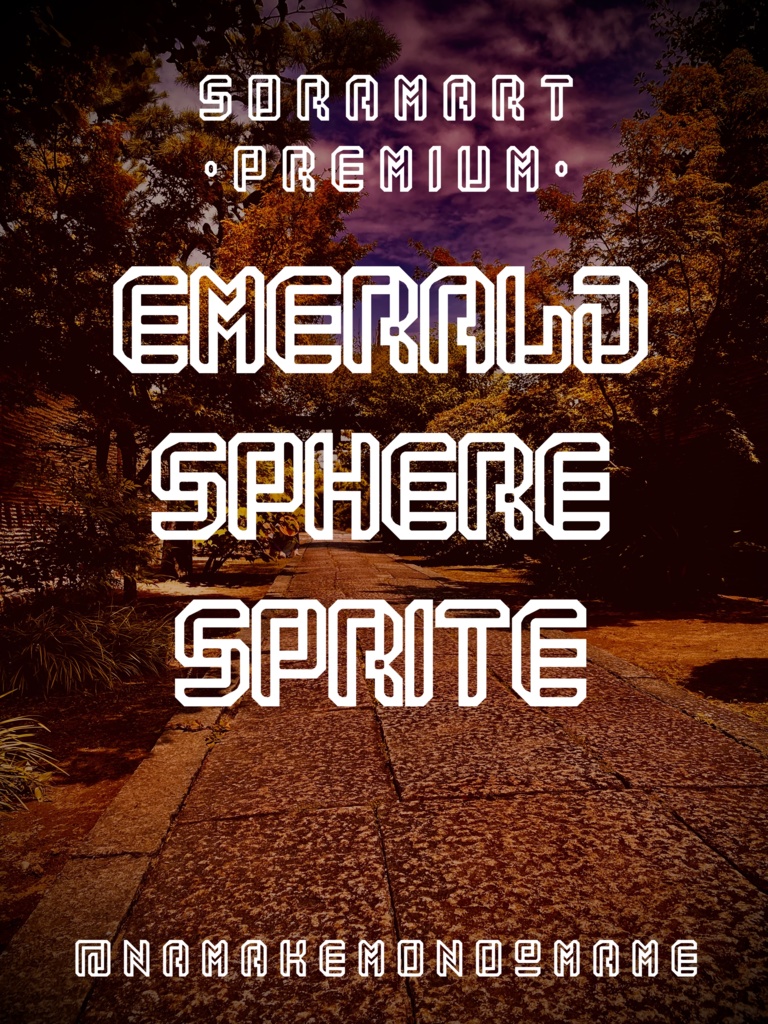
そらマートフォントデータ”Emerald Sphere Sprite”Digital2,500 JPYAdd to CartBuy a GiftAbout Gift八角形シルエットのポップ調フォントに白抜き加工を施した "Emerald Sphere Sprite" です。 「TrueTypeフォントファイル」という形式です。 ダウンロードした後、Zipファイル内のデータをインストールしてお使いください。 このフォントは商用利用可となっております。 お客様の制作・創作活動のお役に立てれば幸いです。 ※使用上の注意事項などは、添付のReadmeをお読みください。 ※このフォントは、有料販売専用商品です。そらマートVisit FANBOX!Fontsフォントデータ”Eight-bit Quest Wide”そらマート0 JPYFontsフォントデータ”Eight-bit Quest”そらマート0 JPYFontsフォントデータ”Tonik Crate”そらマート0 JPYFontsフォントデータ”Vapor Sprout Edge”そらマート2,500 JPYFontsフォントデータ”Vapor Sprout Wide”そらマート2,500 JPYFontsフォントデータ”Vapor Sprout”そらマート2,500 JPYFontsフォントデータ”Star Shoot Ray”そらマート2,500 JPYFontsフォントデータ”Star Shoot Black Wide”そらマート2,500 JPYFontsフォントデータ”Star Shoot Black”そらマート2,500 JPYFontsフォントデータ”Mars Invader Balloon”そらマート2,500 JPYFontsフォントデータ”Mars Invader Wide”そらマート2,500 JPYFontsフォントデータ”Mars Invader”そらマート2,500 JPYFontsフォントデータ”Rock Cut Serif”そらマート2,500 JPYFontsフォントデータ”Rock Cut Drop Wide”そらマート2,500 JPYFontsフォントデータ”Rock Cut Drop”そらマート2,500 JPYFontsフォントデータ”Longtail Sans Serif Slashed”そらマート2,500 JPYFontsフォントデータ”Longtail Sans Serif Bold”そらマート2,500 JPYFontsフォントデータ”Longtail Sans Serif”そらマート2,500 JPYFontsフォントデータ”Pretty Commando”そらマート2,500 JPYFontsフォントデータ”Abyss Dive Punk Retro”そらマート2,500 JPYSee More